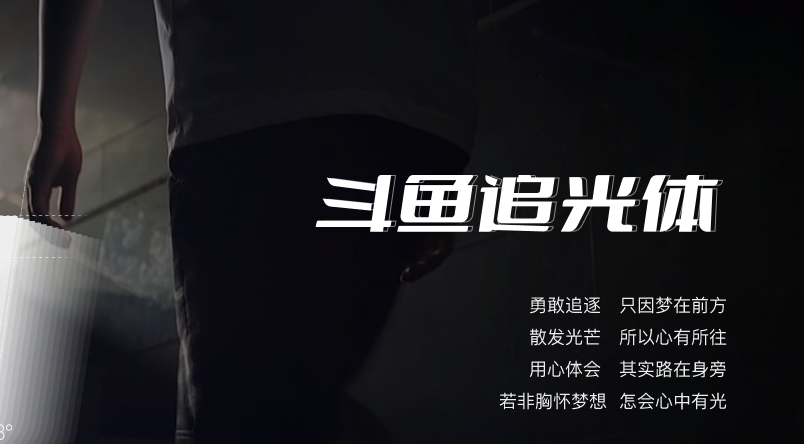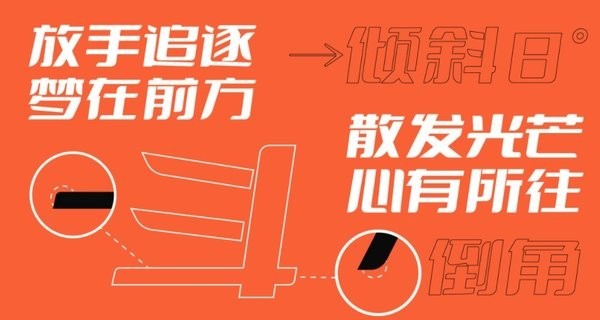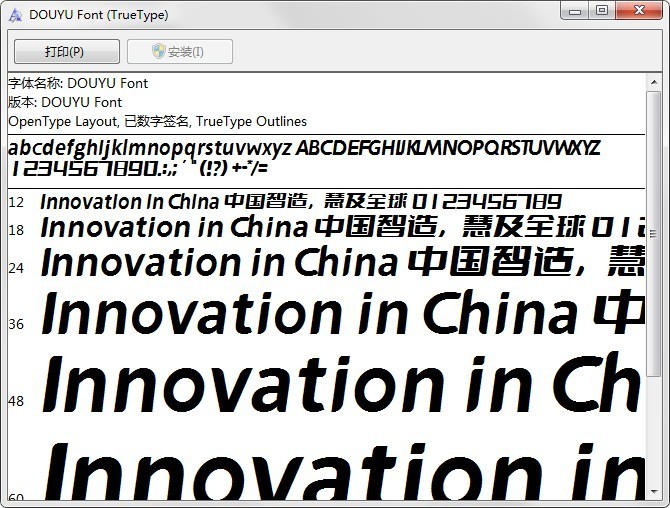
斗鱼追光体字体
斗鱼追光体免费商用版是一款斗鱼旗下设计的个性艺术字体,可以用于商用或者个人、企业免费使用,适用范围十分广泛,广告设计、海报设计、包装设计等都能使用。还蕴涵独特意义,表达勇往直前、追逐梦想,向前冲的情感,喜欢的伙伴们可不要错过!
斗鱼追光体字体简介:
斗鱼追光体,是由斗鱼武汉研发部UED提供指导,品牌组设计成员主导设计的全新品牌字体。是符合GB2312简体中文编码字符标准的专属品牌字体。是拥有一种标准版字重,包含6763个中文字符,100个西文及数字符号。随着斗鱼品牌场景的日益丰富,斗鱼追光体能逐渐适配平台的各种场景。
斗鱼追光体ttf特点:
-- 文字呈现右倾斜,代表着一种勇往直前、奔跑冲向梦想的含义
-- 可以用于影视、广告、包装等等领域